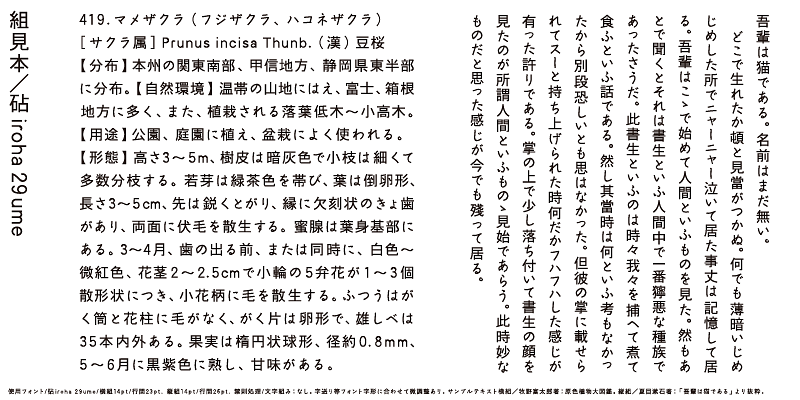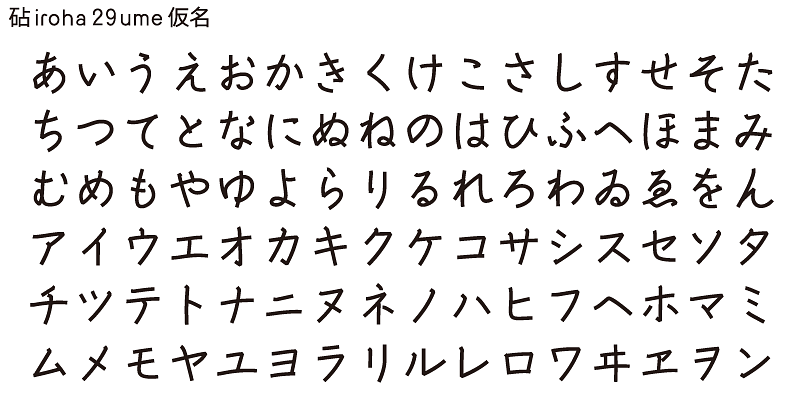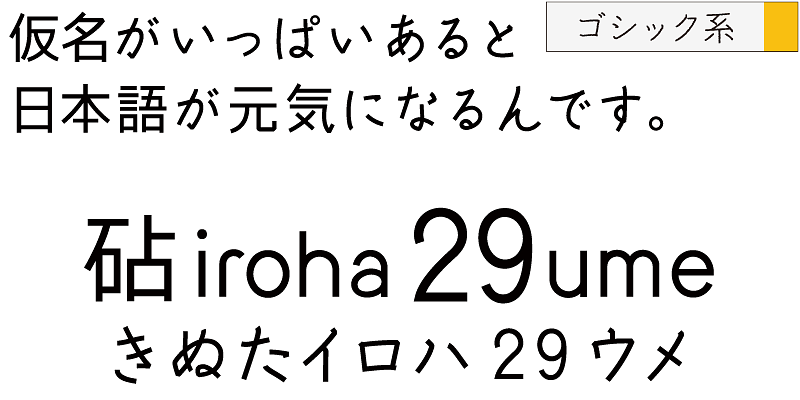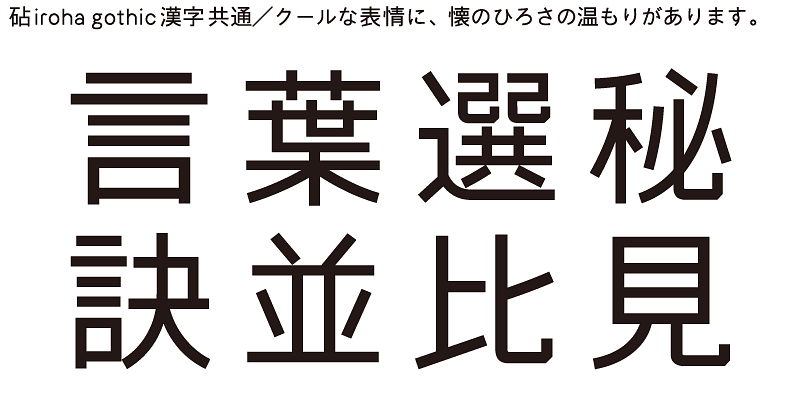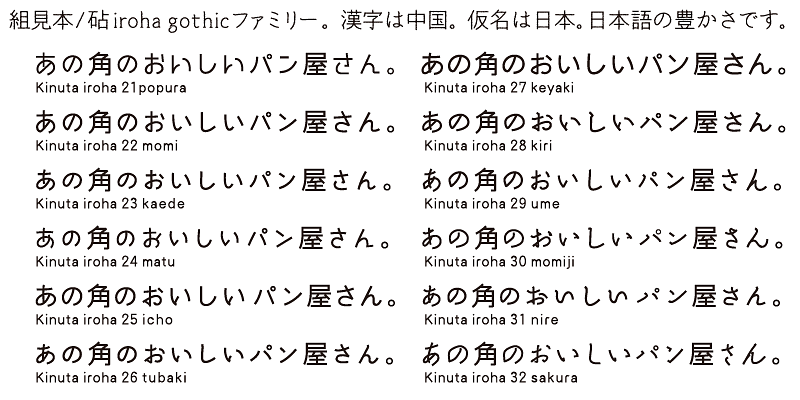
Iroha 29ume a une maturité tempérée par une subtile douceur pour une lecture élégante.
Les mêmes caractères idéographiques (kanji) sont partagés par toutes les variantes Iroha. Les caractères Kanji d’Iroha sont conçus avec des traits linéaires et des structures simples. Il existe 12 variantes de kana.
L’une des particularités de la langue japonaise réside dans son utilisation de caractères syllabiques, les kana. Ceux-ci ont été inventés au Japon pour représenter les sons du japonais et traduire les textes importés de Chine. Ce sont eux qui permettent de créer des mots et des expressions japonais à partir de caractères idéographiques (kanji ou caractères chinois). Même s’ils peuvent présenter des ambiguïtés, ces mots et expressions témoignent de la chaleur et de la douceur de la vie des habitants de ce petit pays densément peuplé qu’est le Japon.
Kinuta Font Factory estime que les kana sont à l’origine même de l’écriture du japonais, et nous pensons que les améliorer peut contribuer à donner encore plus de charme aux textes japonais. En moyenne, 60 % des écrits japonais sont consitués de kana. Changer la forme de ces caractères peut donc transformer l’aspect visuel de ces textes. Les possibilités d’expression typographique utilisant des kana simples, dynamiques et curvilignes sont vastes, et la richesse de la langue japonaise écrite repose sur ces caractères. C’est la raison pour laquelle Kinuta Font Factory propose un large éventail de variantes de polices kana.